안병국의 웹타이포그래피 – 손글씨체와 캘리그라피의 웹디자인 활용
산돌의 ‘백종열체’와 윤디자인의 ‘봄날체’가 등장하면서 웹디자이너들에게 보다 확장된 컨셉트를 효율적으로 전달할 수 있는 길이 열렸다. 즉, 그 자체로 세련미를 가지면서도 다른 디자인 요소들과 조형적으로 조화가 잘 되는 폰트의 등장은 고객과의 감성 커뮤니케이션을 중시하는 사이트에서 효과적으로 이용할 수 있기 때문이다,
정형화된 폰트에서 벗어나 손 맛이 묻어나는 손글씨 폰트의 등장은 비단 웹디자이너들 뿐만 아니라 타이포그래피가 필요한 다른 디자인 분야에서도 매우 반가운 일이 아닐 수 없을 것이다. 물론 봄날체나 백종열체 이전에도 손글씨 폰트가 없었던 것은 아니다. 그러나 대부분의 손글씨 폰트가 모든 세대에 어필할 수 있을 만큼의 객관성은 지니지 못했던 것은 사실이다.
가독성이나 판독성을 중시하기 보다는 글꼴 자체의 형태와 감성 코드를 담아내기 위한 노력에 치중하다 보니 지극히 개인적인 용도 외에는 사용하기 어려웠을 정도로 대중적으로 인기를 끌어내는 데는 실패해왔다. 또한 어떤 분야보다 대중성과 사용성을 중시하는 웹디자인에서는 사이트 퀄리티를 저해하는 폰트로 인식될 만큼 손글씨는 철저히 외면당해 왔다. 하지만 가독성과 판독성 그리고 세련된 멋을 함께 풍기는 폰트의 등장으로 웹디자인에서도 손글씨체의 사용은 큰 전기를 맞게 된다.
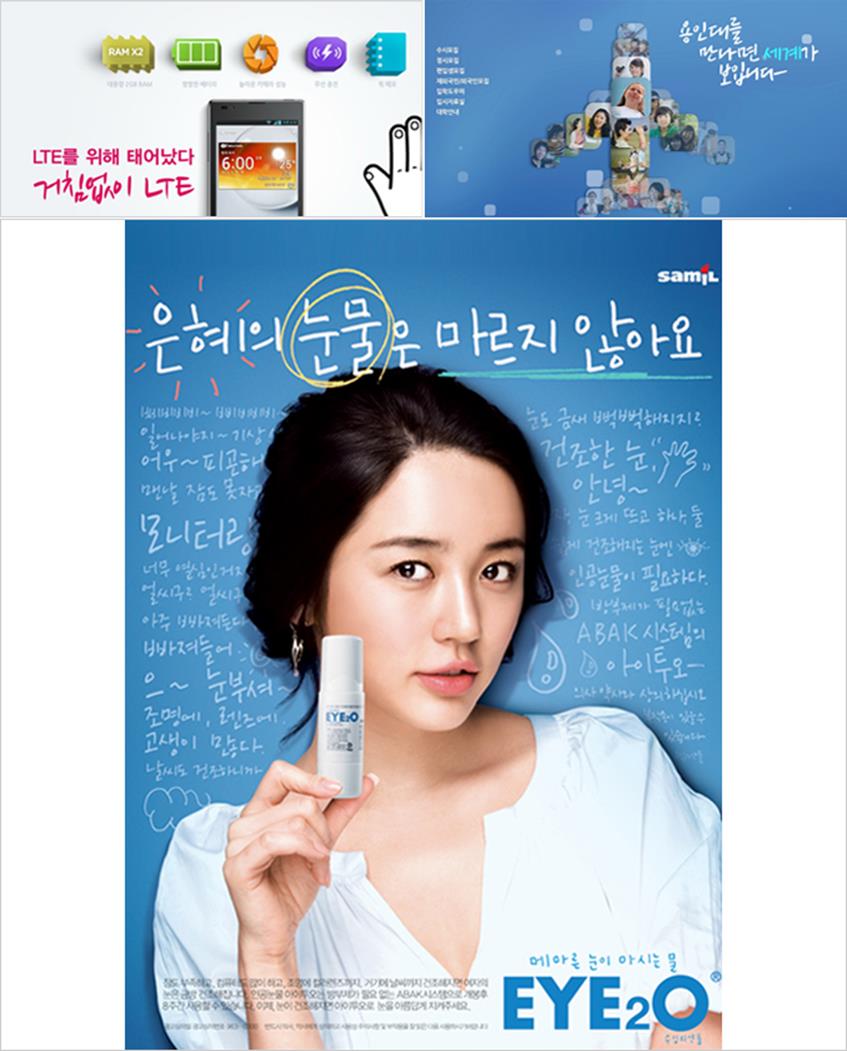
이후 백종열체와 봄날체가 독식하고 있던 손글씨 폰트 시장에 네이버가 무료로 배포하기 시작한 나눔 손글씨가 등장하면서 3파전 양상으로 바뀌었다. 무료라는 힘을 등에 업고 나눔 손글씨 사용 빈도수는 점점 많아지는 양상을 보였다. 하지만 나눔 손글씨 이후 이 세 서체를 대신할 수 있는 손글씨 폰트가 나타나지 못하면서 국내 웹사이트들은 세 개의 폰트를 이용해야 하는 제한된 선택을 할 수 밖에 없게 된다. 영문 서체에 비해 한글 손글씨 폰트가 워낙 부족하다 보니, 처음에는 신선하고 재미있게 다가왔던 이 서체들도 너무 많은 곳에서 보편적으로 사용되다 보니 식상함이 느껴질 정도가 되었다.
이러한 식상함을 탈피하기 위해 많은 웹디자이너들이 마우스 대신 직접 붓을 잡고 캘리그라피에 도전한다거나 자기만의 스타일이 가미된 손글씨를 만들어 디자인에 활용하고 있다. 그러나 타이포그래피와 글자에 대한 깊은 고민과 연구 없이 무분별하게 쓰이는 손글씨나 캘리그라피는 개성은 중시될 수 있지만, 사이트 디자인의 전체적인 퀄리티를 깎아먹을 수 있는 위험요소를 지니고 있음을 인지해야 한다. 단지 유행에 편승해 사이트의 컨셉트 또는 타깃의 성향, 컨텐츠의 내용과 동떨어진 손글씨나 캘리그라피의 사용은 타이포그래피에 대한 스스로의 발전을 가로 막는 독이 든 성배가 될 수 있음을 유의해야 할 것이다.
손글씨 폰트를 활용할 때 유의해야 할 부분들
손글씨 폰트는 글자와 글자 사이의 크기나 형태 변화가 일반 폰트에 비해 심하기 때문에 너무 많은 변화를 주게 되면 가독성이나 판독성이 떨어진다. 또한, 안정되어 있는 전체 비주얼의 균형을 깨뜨릴 수 있는 위험요소를 안고 있다. 아래 프렌치 카페 프로모션 사이트에 쓰인 ‘커피를 바꿀 새로운 이유, 프림이 다른 프펜치카페 믹스’라는 타이틀 역시 하단의 내용에 그리드를 무리하게 맞추려 하다 보니 자간이 매우 넓어졌다. 이로 인해 전체적으로 산만한 느낌을 풍기게 되었다. 타이틀 문구에 사용자의 시선을 집중하도록 만드는데 실패해 하단 컨텐츠로의 자연스러운 시선 유도를 방해하고 있다.
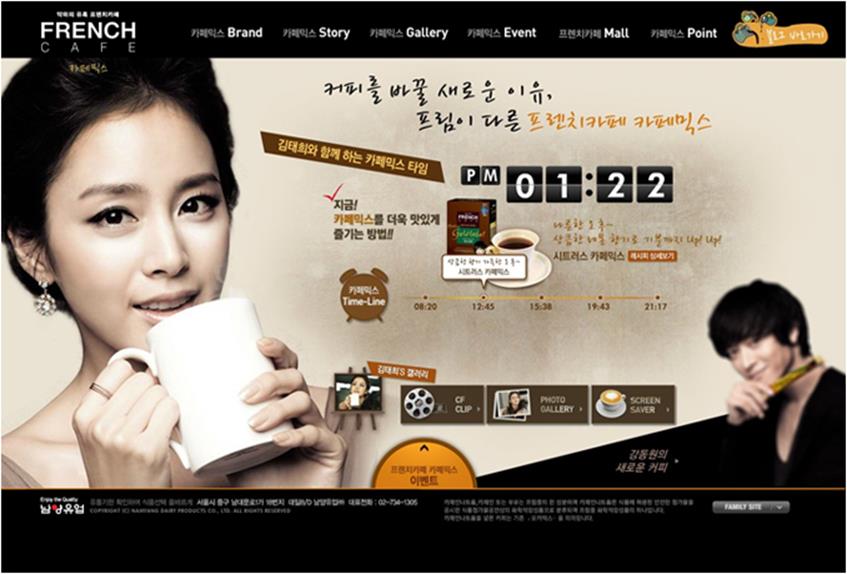
리듬감이 있고 변화가 심한 손글씨를 사용할 때에는 그 변화가 인위적이지 않게 하고 다음 글자로 자연스럽게 넘어갈 수 있도록 해주어야 하는데 자간을 너무 넓히다 보니 타이틀이 문장으로 읽히지 못하고 한 글자 한 글자 띄엄띄엄 읽히게 만들었다. 즉, 타이포그래피에 있어 안정적인 균형감과 리듬감을 이끌어 내기 위해서는 그룹화된 것들과 그렇지 않은 것들에 대한 확실한 시각적 처리가 우선시 되어야 한다.
또한 손글씨 폰트는 일반 폰트 크기를 감안해 그 크기를 예상하면 오산이다. 일반 폰트와 같은 크기로 손글씨 폰트 크기를 설정하더라도 고딕계열이나 명조계열 폰트에 비해 손글씨 폰트 크기가 상대적으로 작게 처리되기 때문에 포토샵에서 설정하는 폰트 크기를 절대적인 기준으로 삼아 처리해서는 원했던 느낌을 얻을 수 없을 것이다.
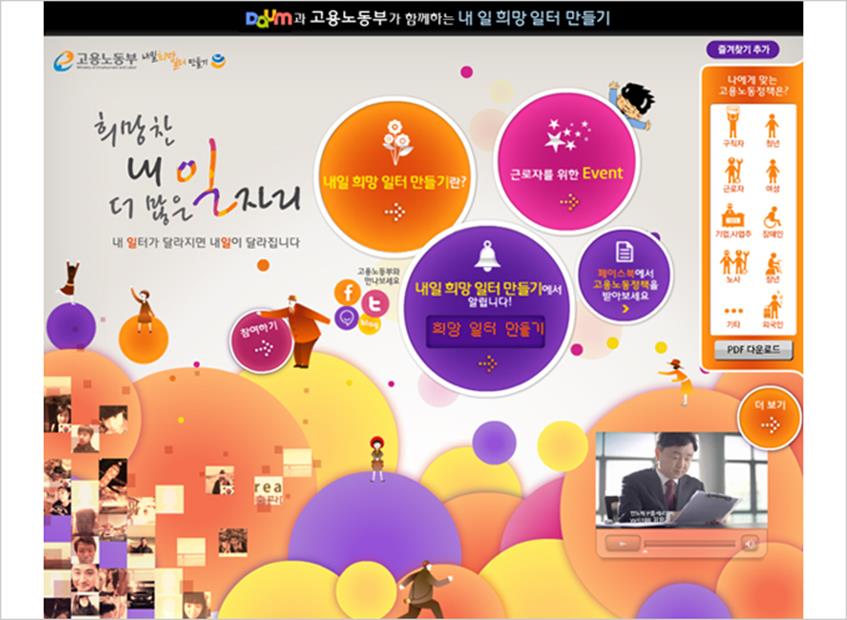
위 사이트 역시 자간 간격은 앞에서 언급했던 사이트와는 달리 안정되게 설정되어 있지만 단어 단위로 컬러나 음영에 있어 너무 많은 변화가 있다 보니, 산만하게 느껴질 수 밖에 없다. 다른 주변의 디자인 요소들 없이 타이틀만 단독으로 활용되었다면 글자 변화를 통해 재미 요소와 동적인 느낌을 가미할 수 있었겠으나, 주변 요소까지 너무 화려한 나머지 어느 부분에도 집중되지 못하는 불편한 시각 효과를 보여주고 있다.
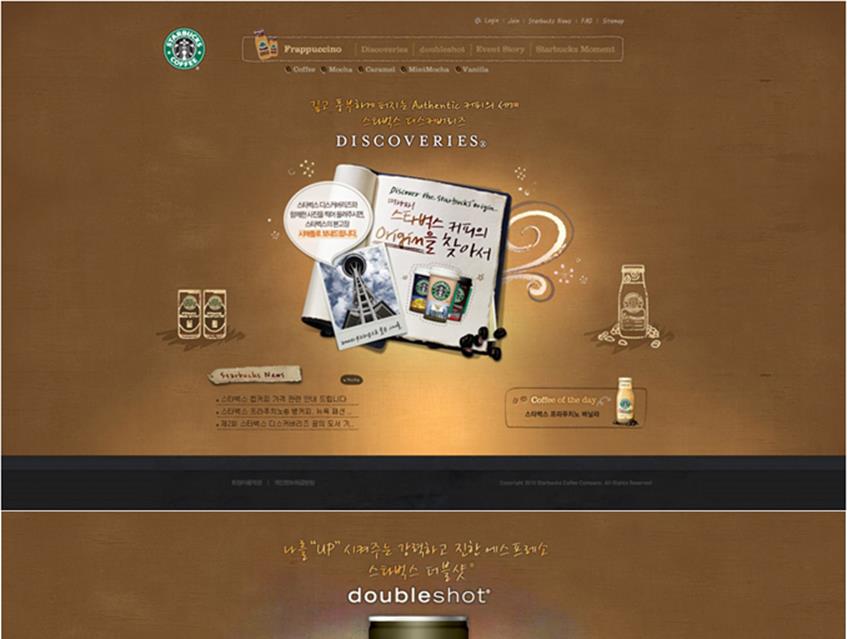
또 다른 사례를 살펴보자. 커피를 컨텐츠로 하는 위 사이트는 전체적인 디자인 완성도나 퀄리티가 굉장히 높은 편이다. 그 사이에서 미미한 차이를 발견할 수 있는데, 손글씨 폰트를 적절한 크기로 사용했는지에 따른 효과적인 정보 제공이 바로 그것이다. 먼저 스타벅스 사이트에서는 ‘DISCOVERIES’라는 문구를 기준으로 상단에 봄날체로 된 보조 타이틀 문구를 넣고 하단에 백종열체로 된 타이틀 문구를 사용했다.
물론 커피에서 느껴지는 감성을 전달하기 위해 손글씨를 활용했겠지만, 분위기가 다른 두 서체를 굳이 함께 쓴 의도가 분명하지 않다. 또한 상단의 봄날체로 쓴 문구는 크기가 너무 작고 그림자 효과까지 더해져 내용을 읽기에 어려울 정도다. 멋스러움을 살리려다 결국 텍스트를 읽기 어렵게 만들었고 전체 컨셉트도 다소 혼란스럽게 하는 결과를 초래했다. 차라리 보다 안정적으로 느껴지도록 고딕계열 폰트를 사용했다면 가독성과 안정성 모두 확보할 수 있지 않았을까.
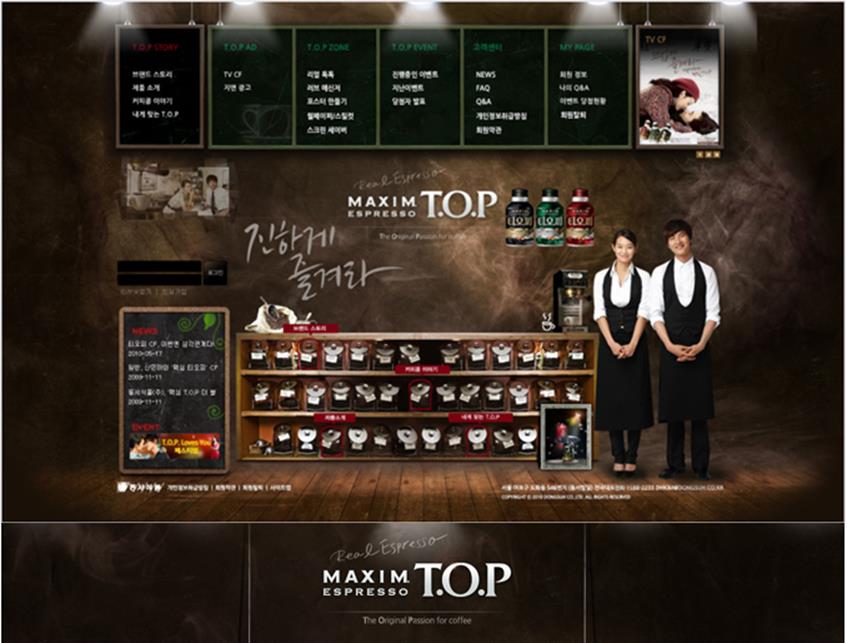
상대적으로 위에 보이는 맥심 TOP사이트는 버리는 것과 얻고자 하는 것에 대한 구분이 명확해 보인다. ‘진하게 즐겨라’라고 직접 쓴 캘리그라피 크기가 안정적으로 들어가 헤드카피로서의 역할을 충실히 하고 있다. 로고 상단에 들어간 영문 손글씨는 정보로서의 가독성 보다는 낙서와 같은 장식 요소로 활용되고 있다.
두 사례에서 보듯 손글씨 폰트가 가진 변화 외에 추가적인 변화를 주고자 할 때는 더욱 신중해야 한다. 손글씨 폰트가 가진 변화만으로도 이미 많은 율동감과 변화를 보여주기 때문에 효과를 많이 준다고 해서 완성도가 높아지거나 재미있어지는 것이 아님을 유의해야 한다. 또한, 커피 사이트 비교에서 확인했듯 살려야 할 것과 버려야 할 것에 대한 명확한 구분을 통해 전체 디자인 조화와 컨셉트를 잘 유지해 손글씨 폰트의 장점을 극대화해야 할 것이다.